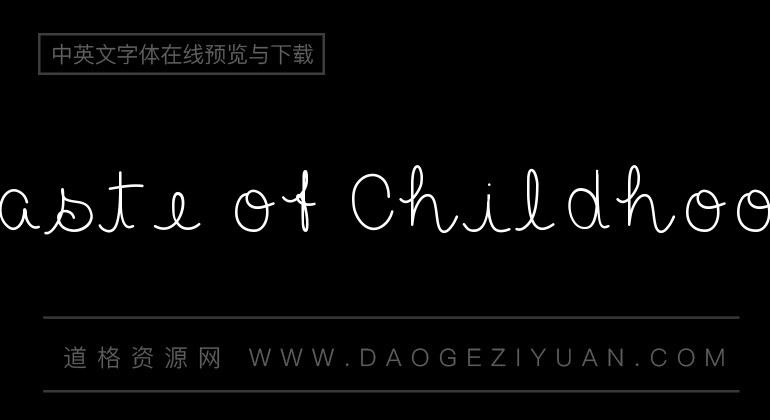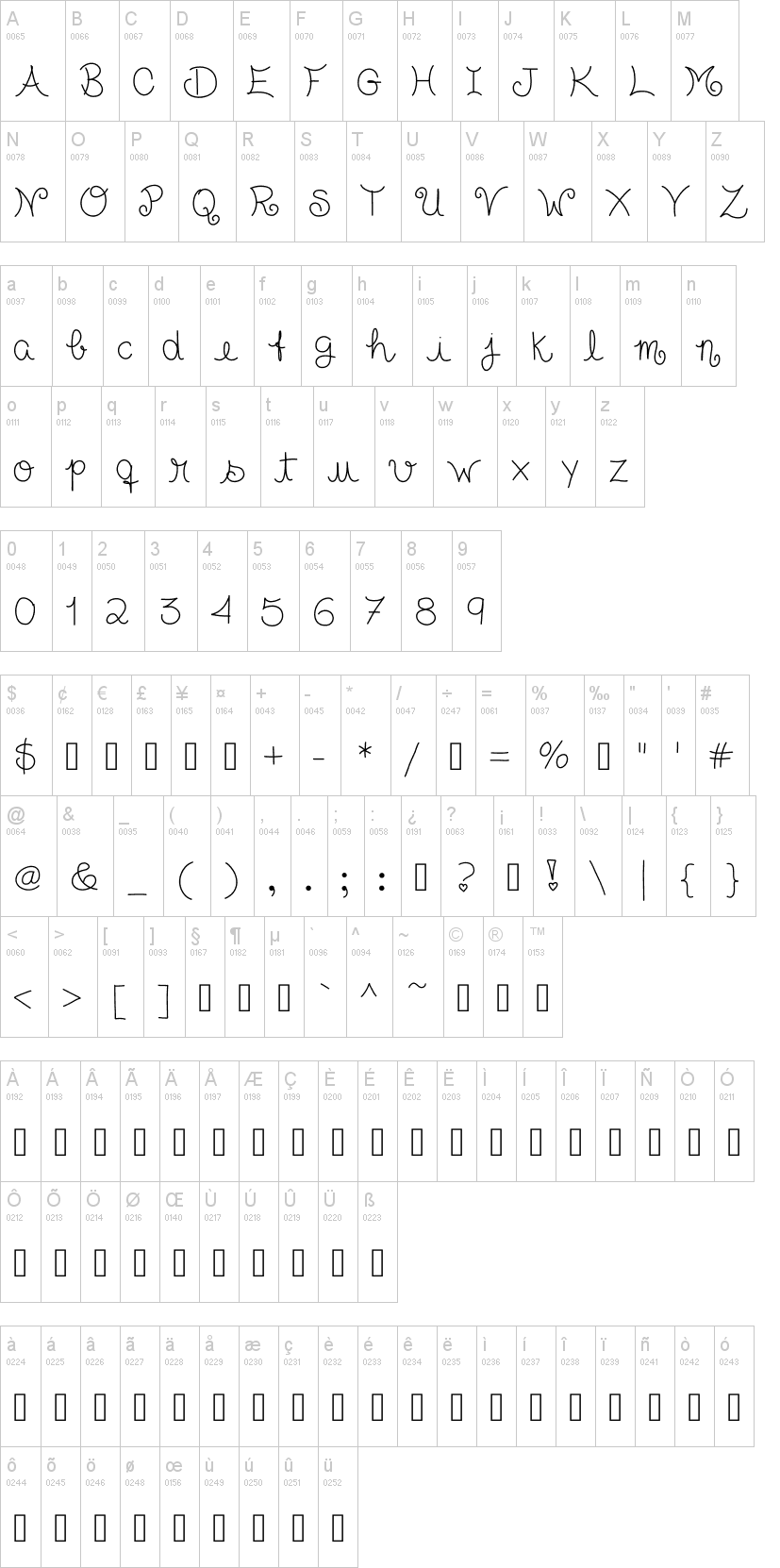
Taste of Childhood是一款充满童趣的手写体字体,由Dana Tanamachi设计,用于给人们带来童年时光的美好回忆。这款字体看起来就像一个孩子用粉笔在纸上乱写一样,可以帮助你把童年时光重新带入现实,也可以用来表达一种温暖的感觉。Taste of Childhood字体是一款充满活力的字体,它的字母有着梦想般的外观,可以让你的文字更有趣,更有活力。内容介绍
Taste of Childhood是一款非常不错的手写艺术字体,具有很好的视觉感,适合于文化类的宣传设计、商业类品牌的广告和产品包装设计以及个性化文字排版等较多场景。